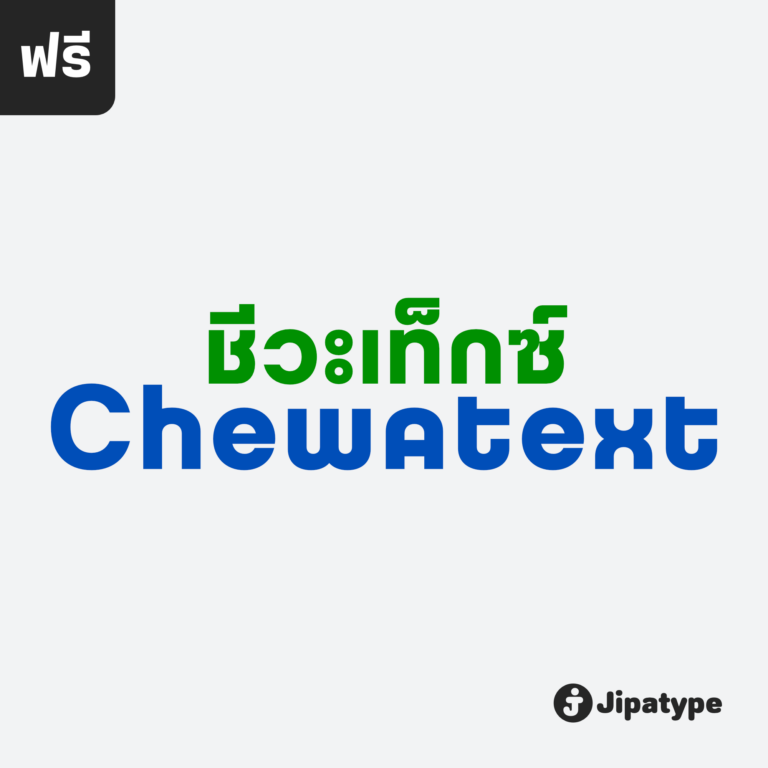
ชีวะเท็กซ์ | Chewatext
Chewatext เป็นแบบอักษรซานเซอริฟที่มีรูปลักษณ์เรียบง่าย เรขาคณิต และเทคโนโลยี มีให้เลือกใช้ถึง 18 สไตล์ รองรับตัวอักษรละติน 1 และอักษรไทย ทำให้เป็นตัวเลือกที่ดีที่สุดสำหรับโปรเจกต์ร่วมสมัย ไม่ว่าจะเป็นงานสิ่งพิมพ์ต่าง ๆ ทั้งออนไลน์และออฟไลน์ ออกแบบโดย : อานุภาพ ใจชำนาญ (Anupap Jaichumnan)สามารถใช้งานฟอนต์ได้ฟรีในเชิงพาณิชย์ ผ่านแอปฯ ของจิปาไทป์ ดูรายละเอียดและดาวน์โหลดแอปฯได้ที่ : jipatype.com